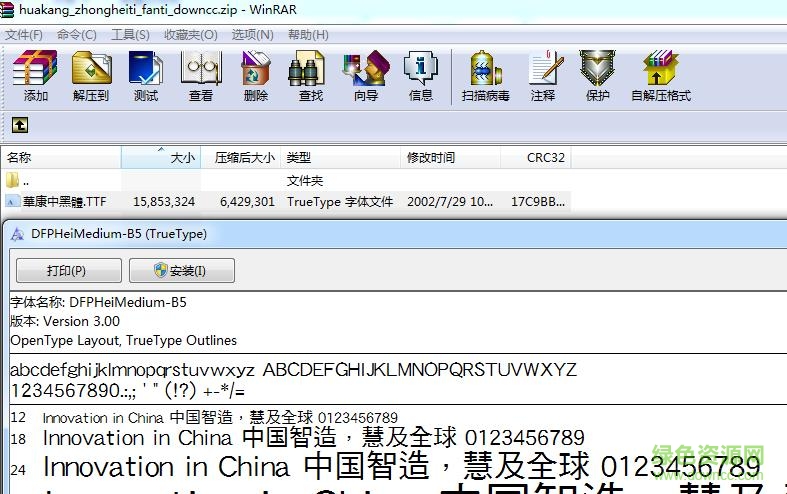
華康中黑體繁體是一款在華康字體中比較不錯(cuò)的字體樣式文件,它具有不錯(cuò)的字體筆鋒,讓人感覺(jué)部分娟秀,同時(shí)能夠運(yùn)用到眾多設(shè)計(jì)當(dāng)中如藝術(shù)字設(shè)計(jì),海報(bào)設(shè)計(jì)等,能夠發(fā)揮出不錯(cuò)的顯示效果!